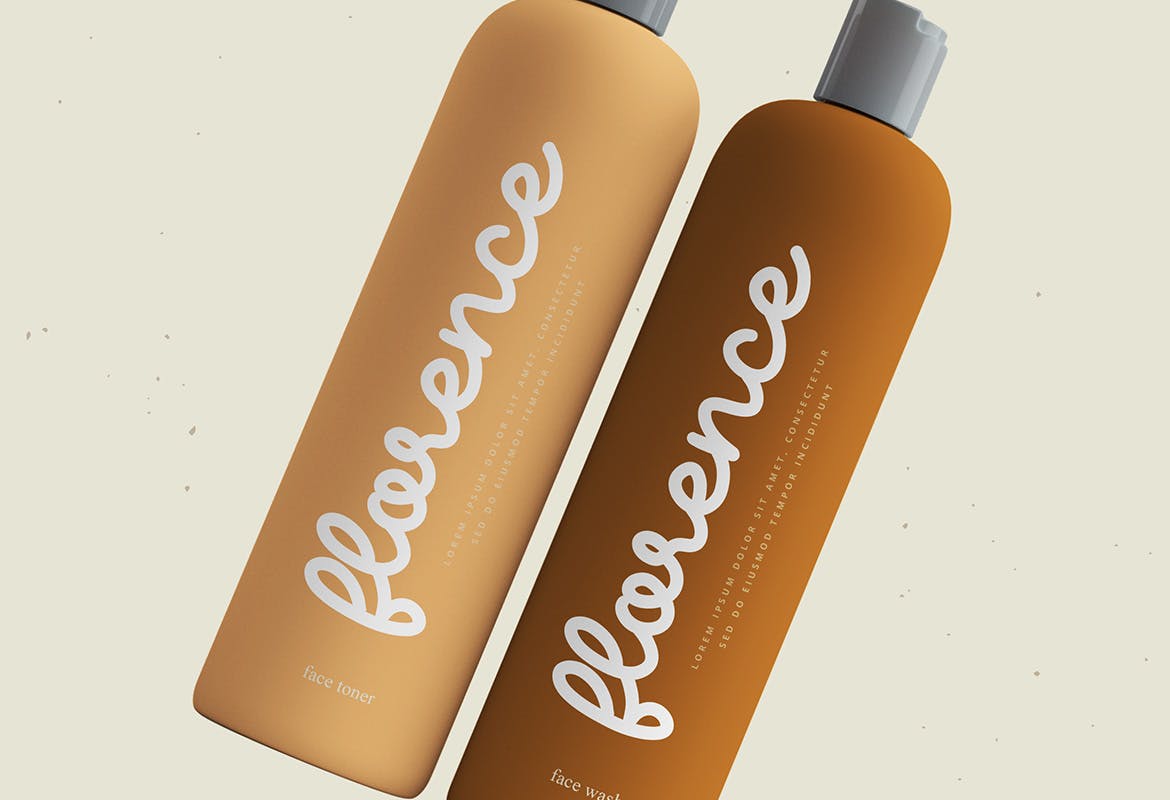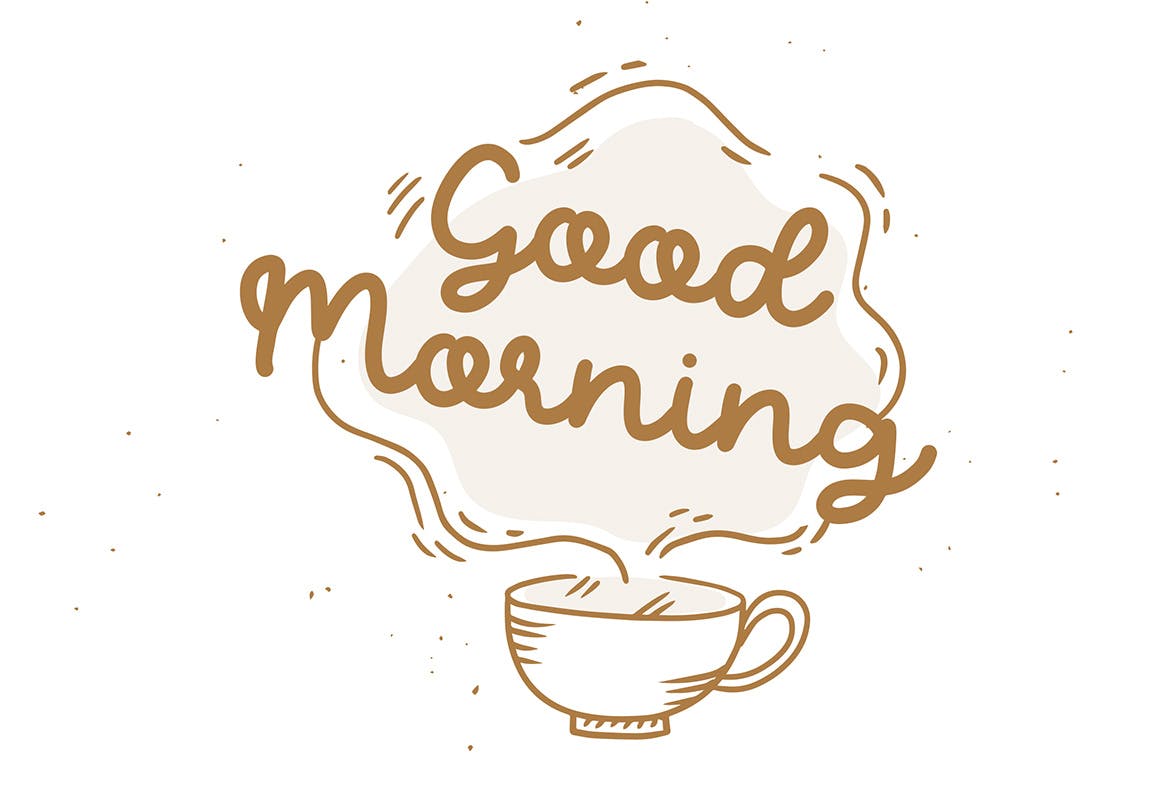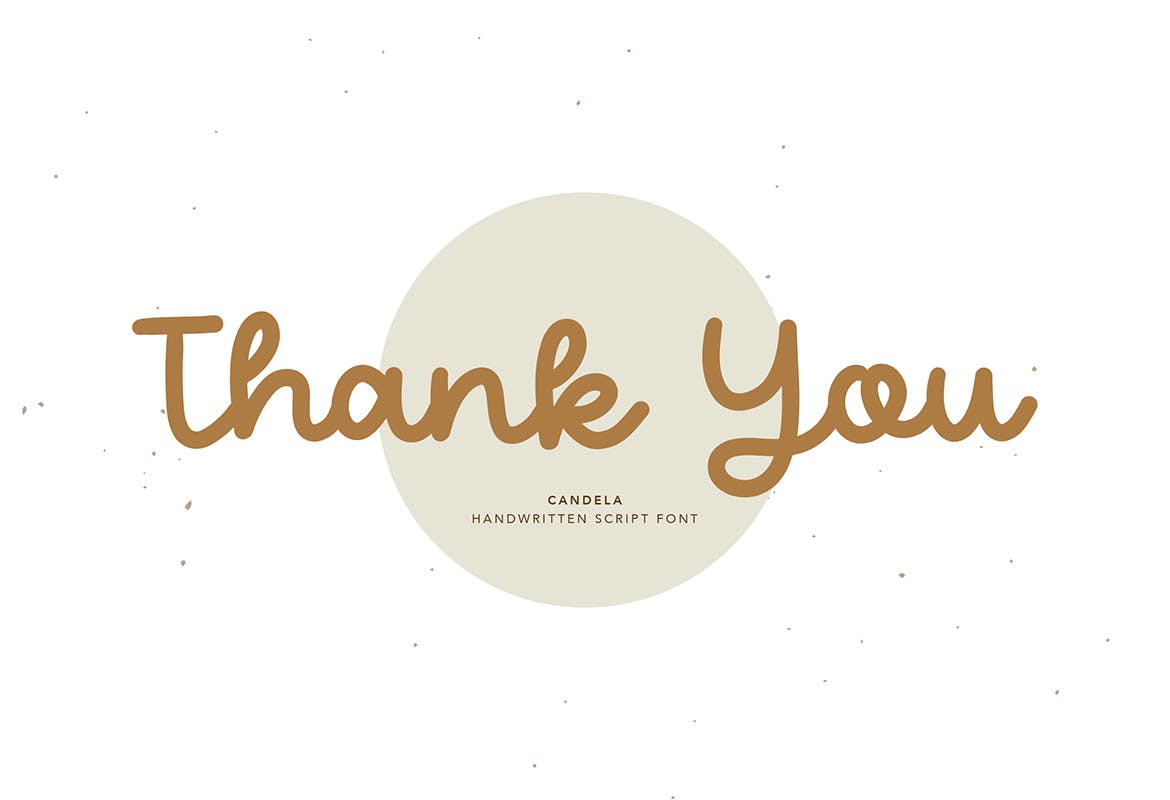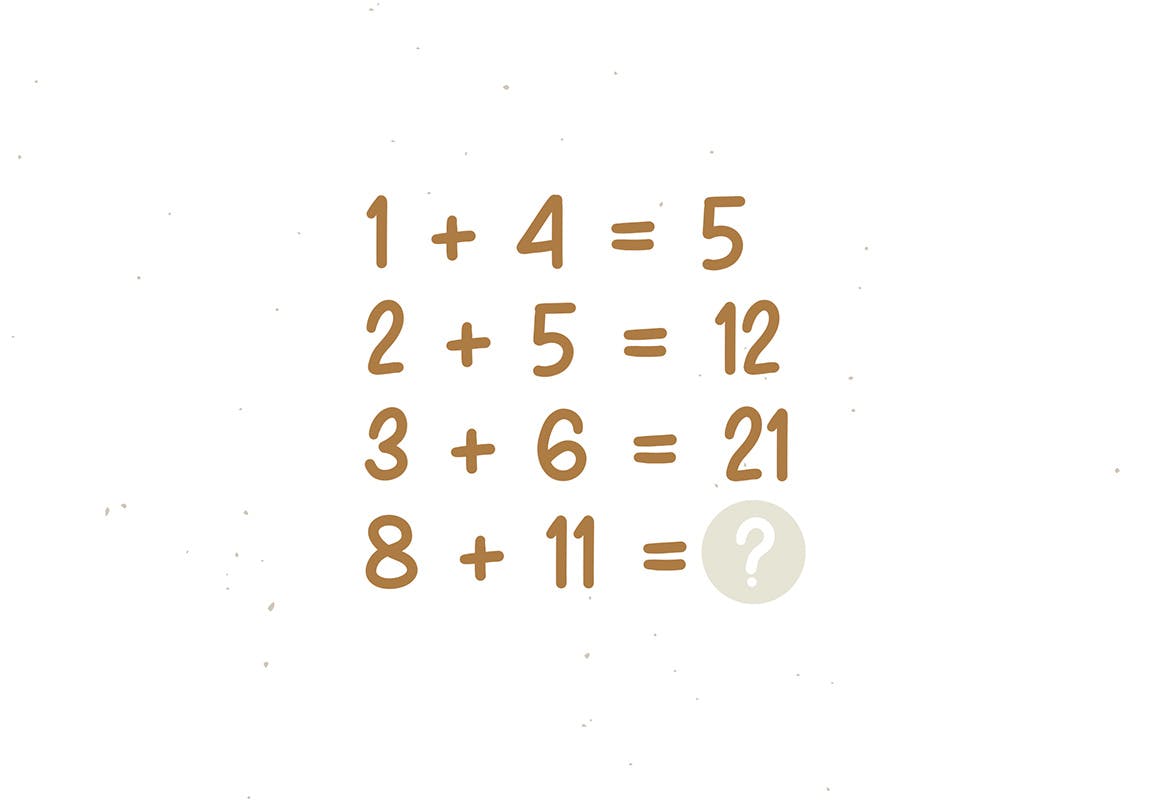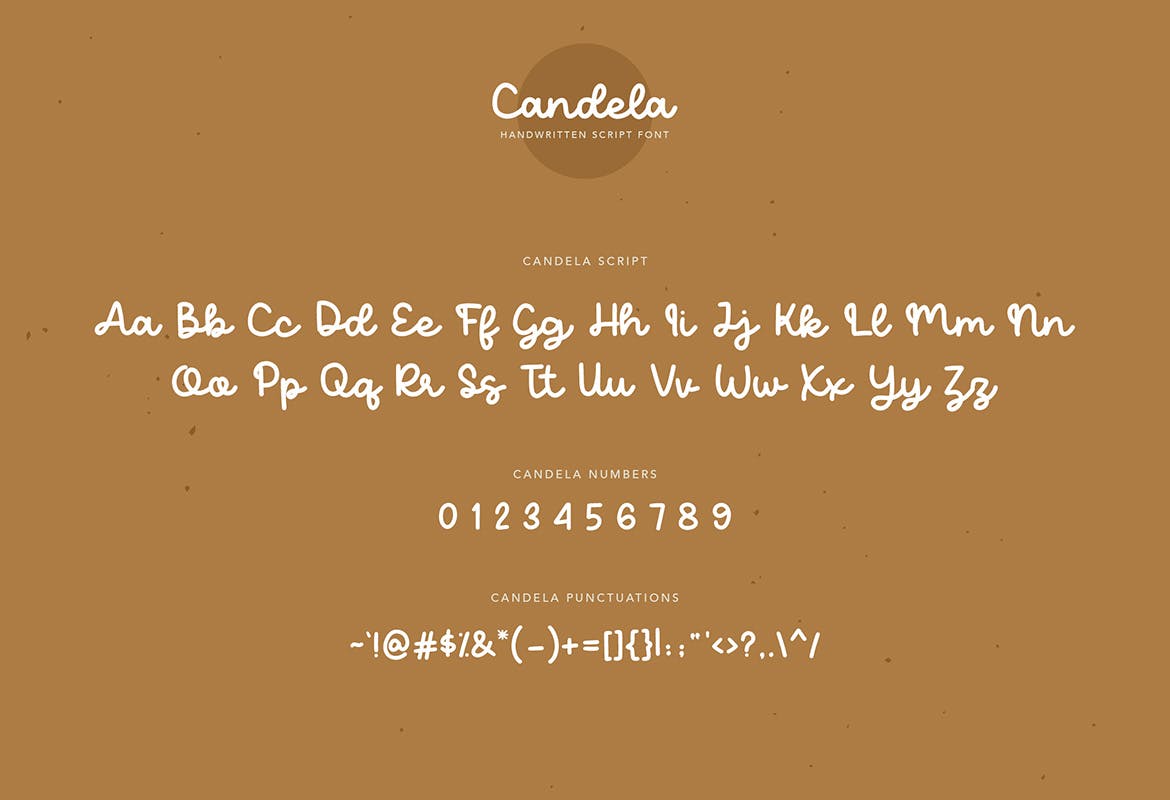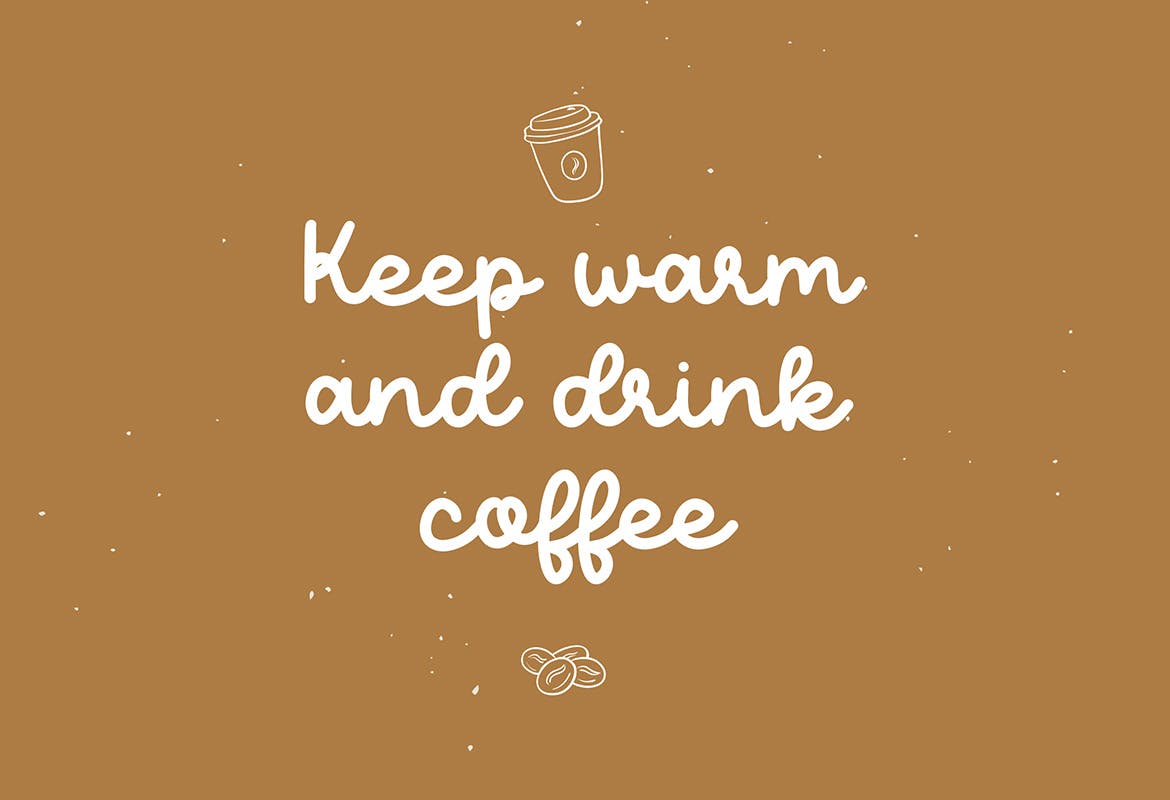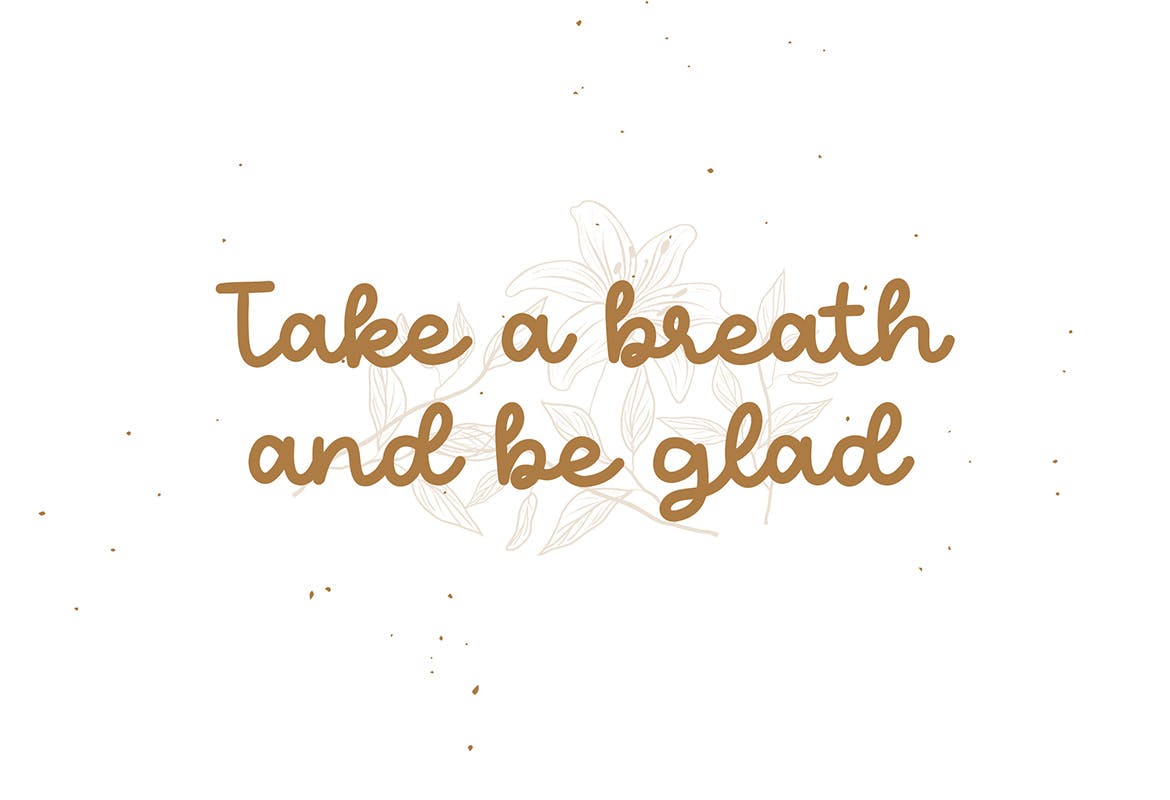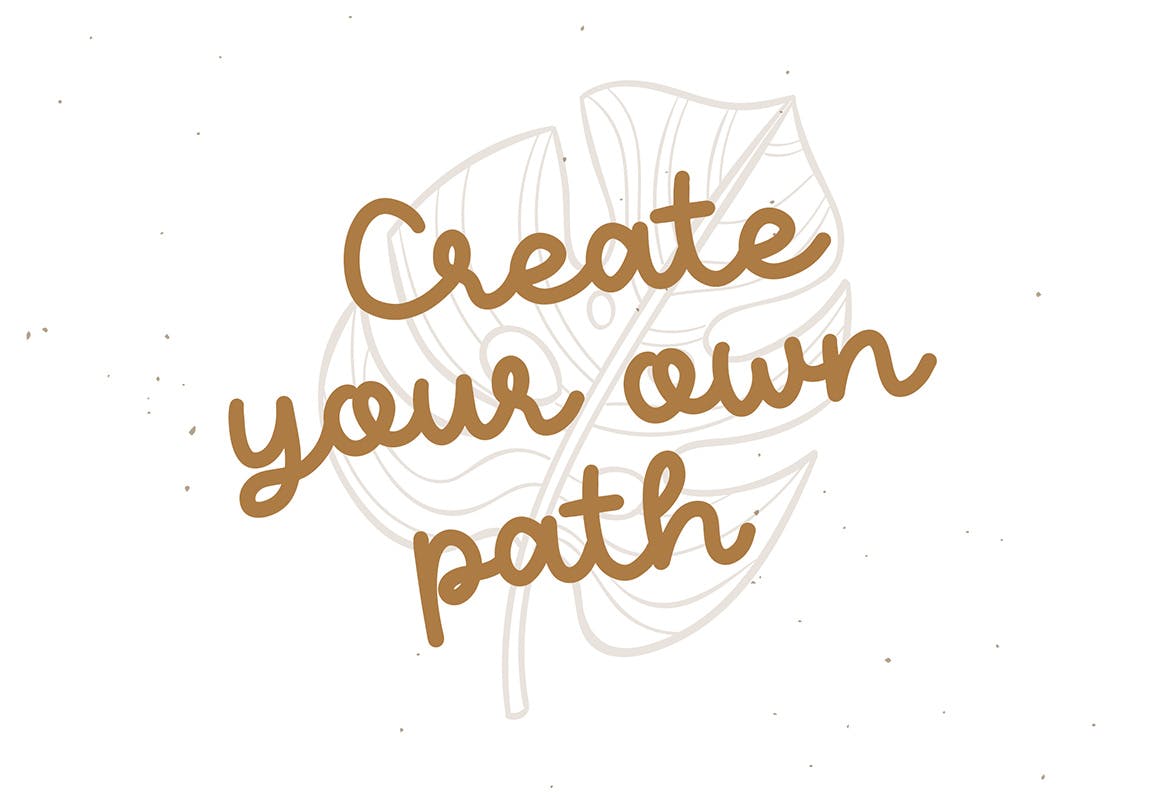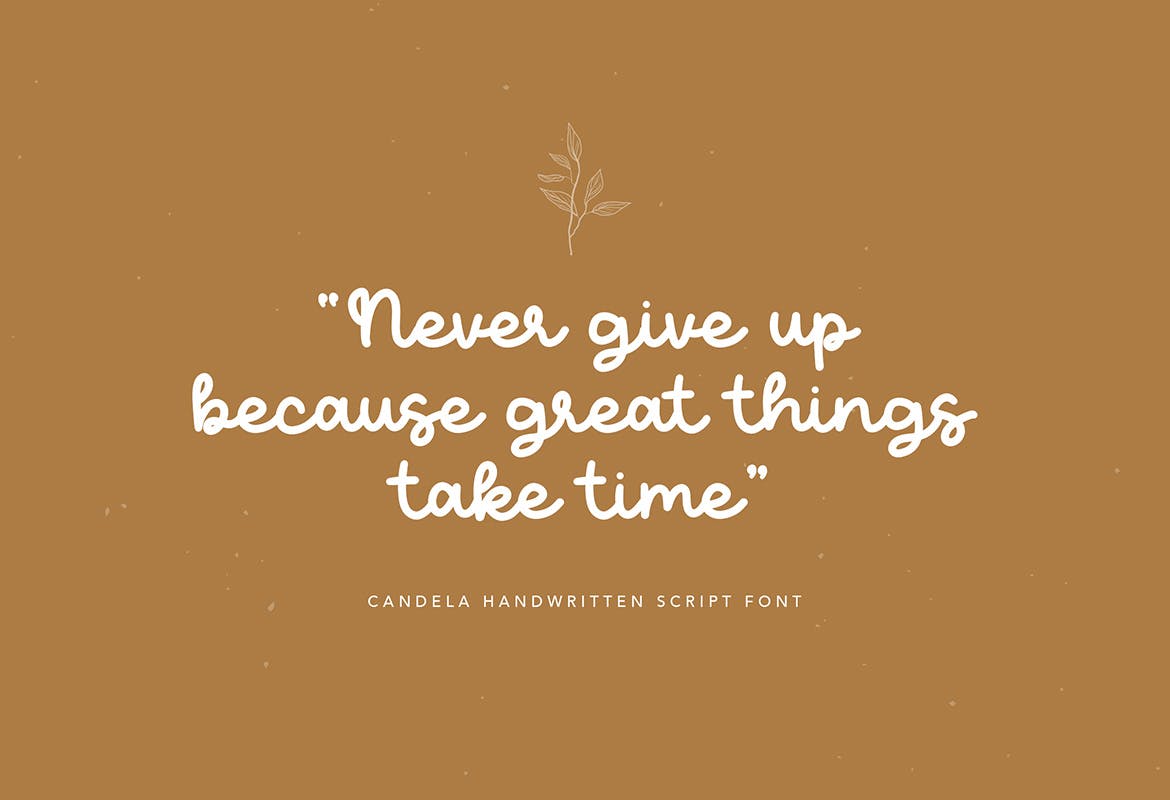
معرفی فونت جدید ما: فونت دستنویس Candela !!! ❤️
فونت Candela یک فونت نرم و شیک دستنویس است که برای پروژههای برندینگ، لوگو، پستهای رسانههای اجتماعی، تبلیغات، متنهای نقلقول، امضا، بستهبندی محصولات، طراحیهای محصولات، برچسب، عکاسی، واترمارک، مد، بوتیک و هر پروژه دیگری مناسب است. این فونت با سطح خوانایی بالا طراحی شده و کاملاً مناسب برای تمهای زیبایی یا متنهای شیک روی هر تصویر پسزمینه است.